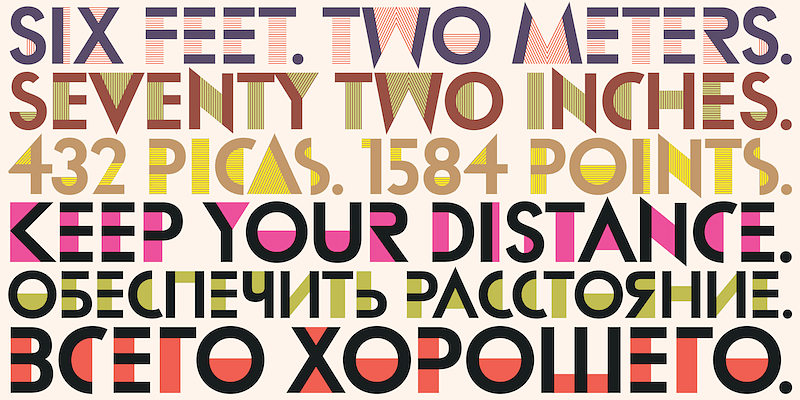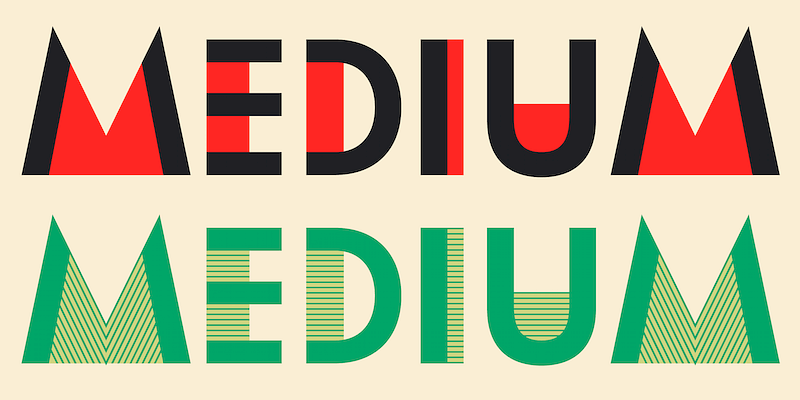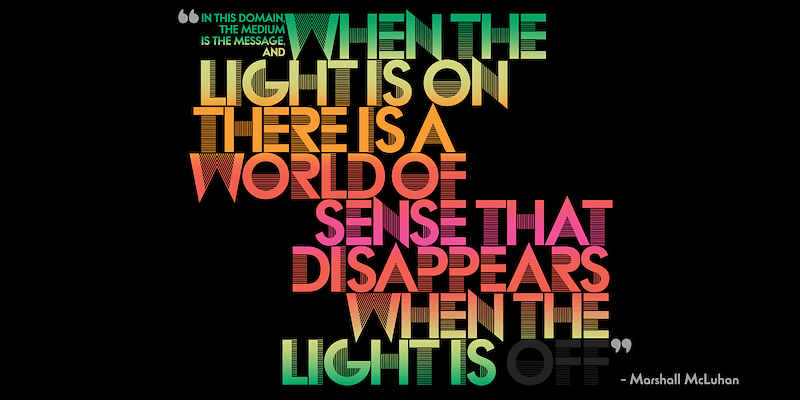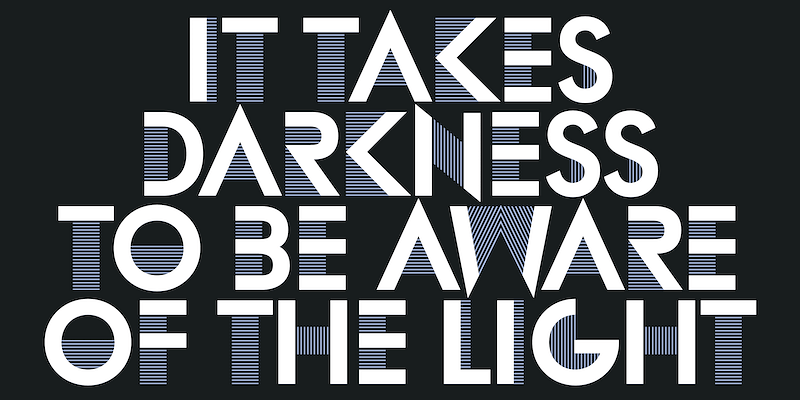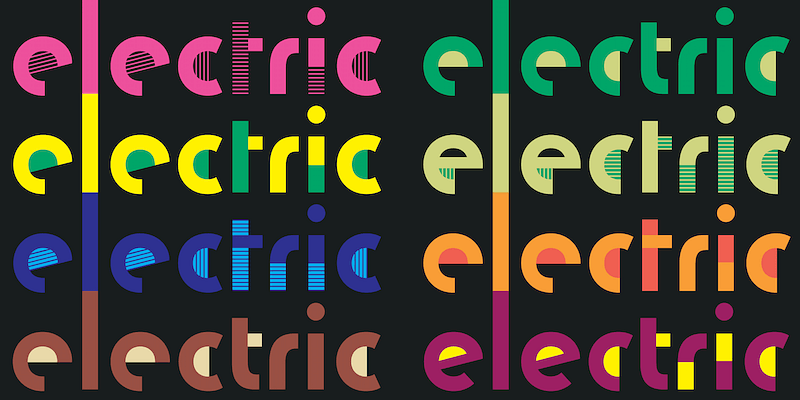
Les formes de cet alphabet sont une variante de Bifur, l’alphabet tout en majuscule conçu par Adolphe Mouron (connu sous le nom de Cassandre) en 1929. Lincoln Electric fait évoluer l’idée de Cassandre en créant de nouvelles formes plus conformes aux principes minimalistes plutôt qu’à la géométrie art déco, ce que l’on retrouve notamment dans les minuscules, qui présentent un lien clair avec les idées du style Bauhaus.